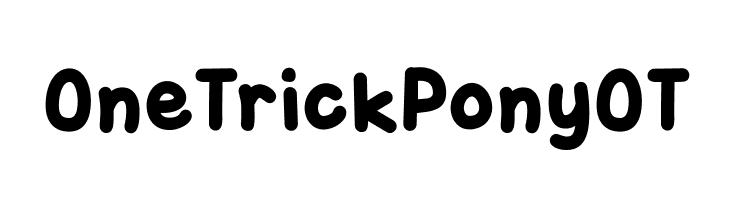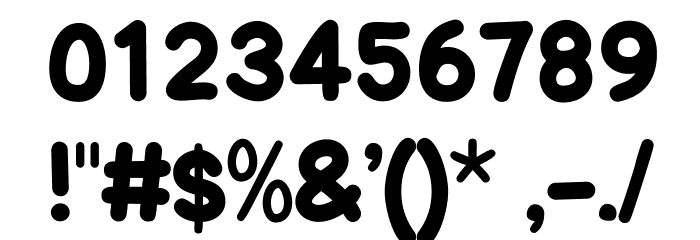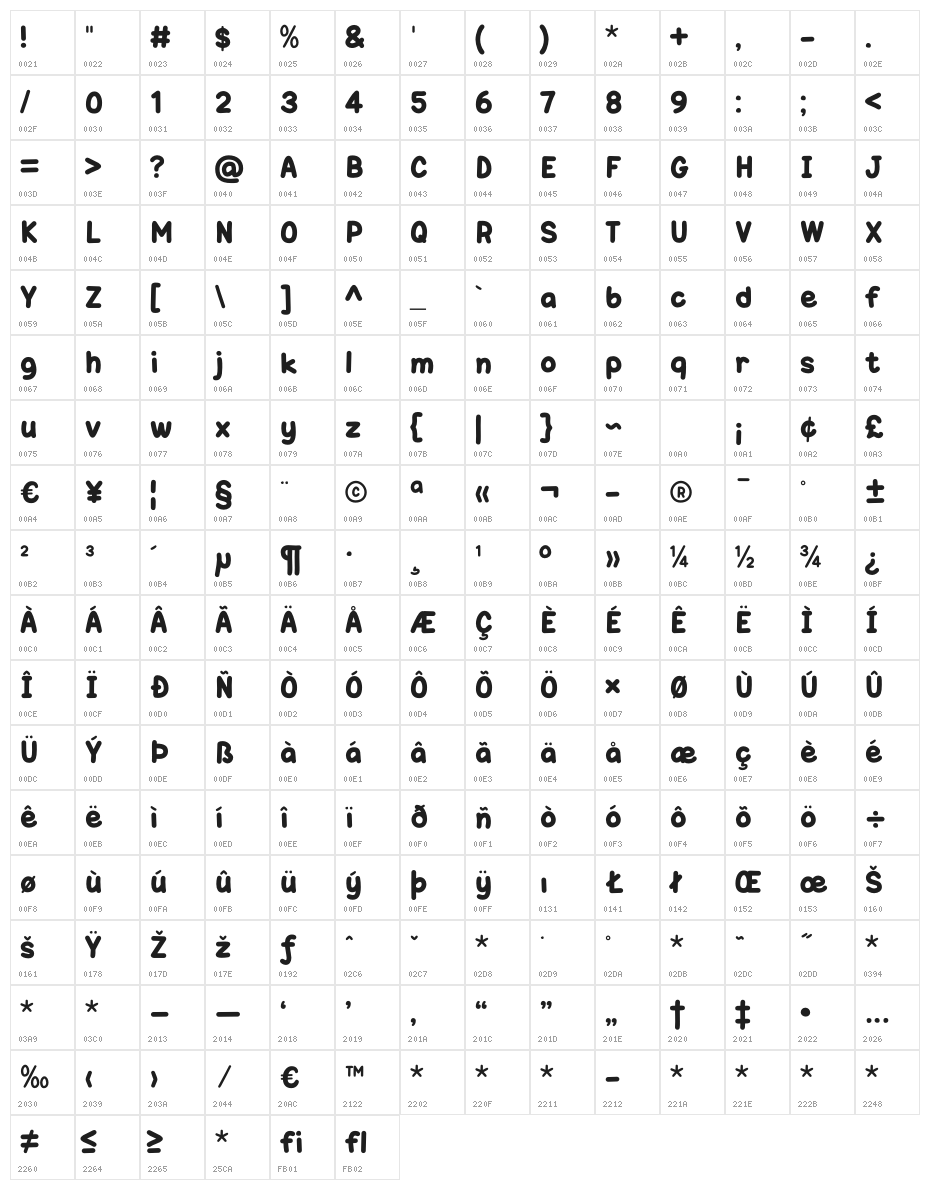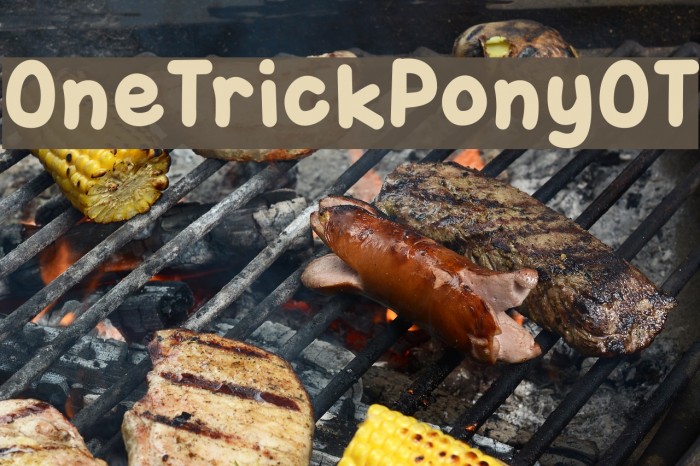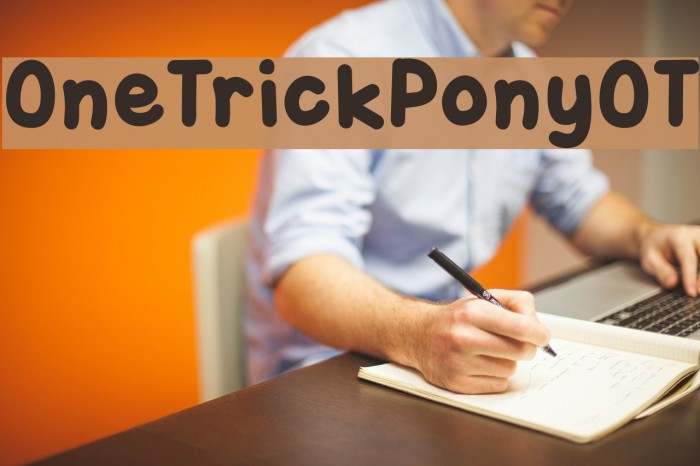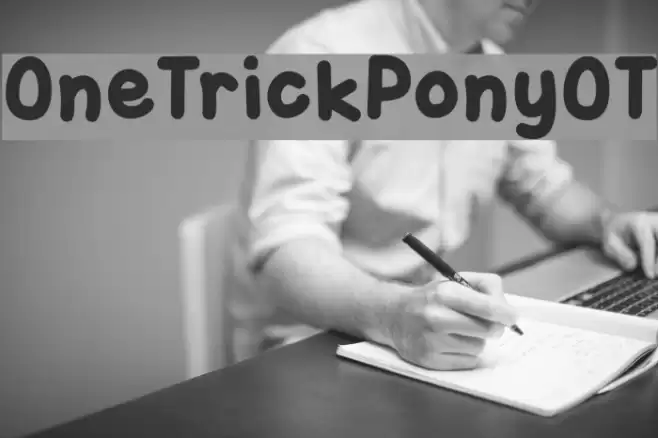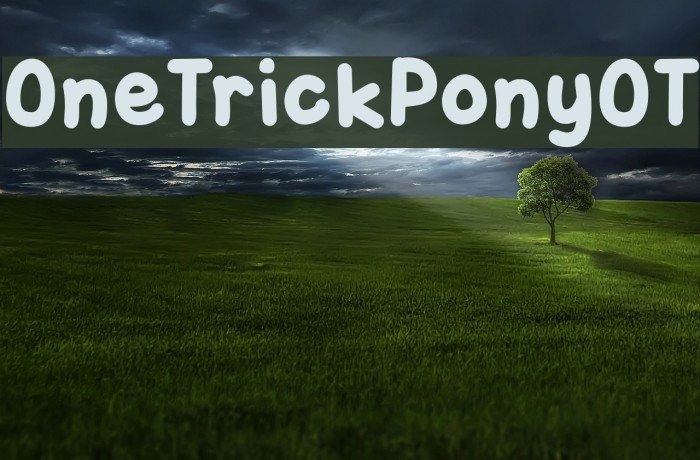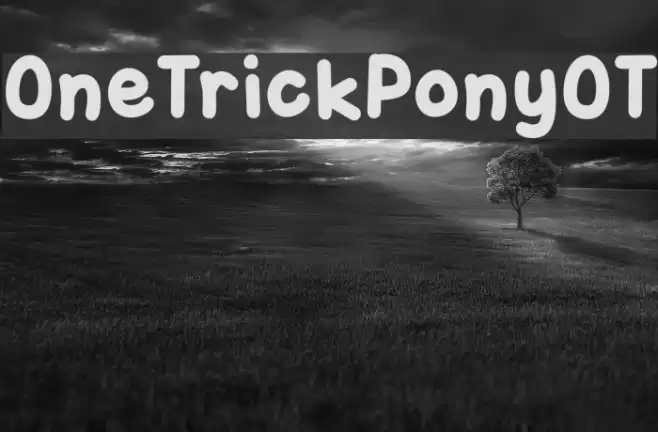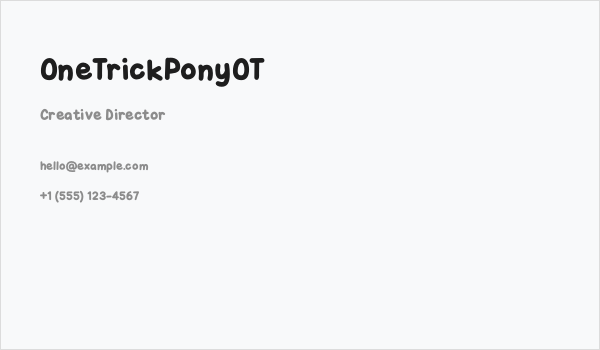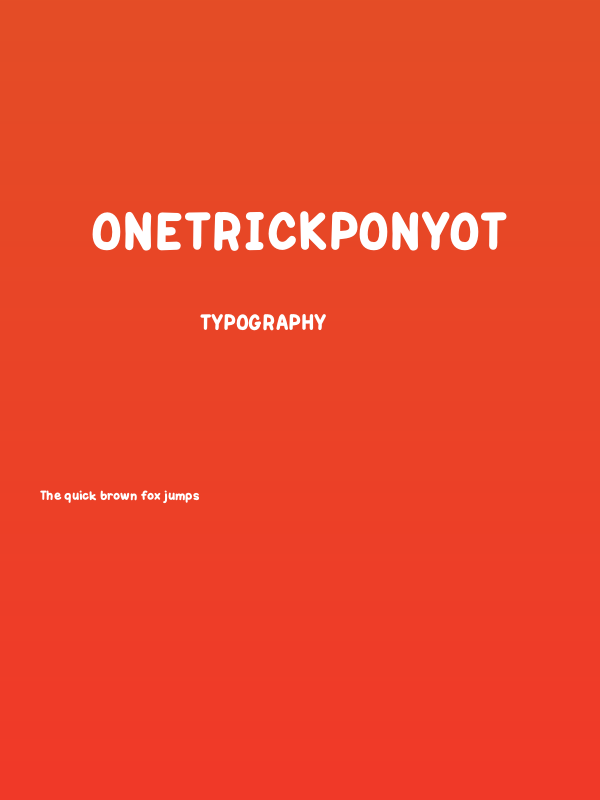
OneTrickPonyOT Font
| Style général | Playful |
| Cas d'utilisation | Headlines, Logos, Informal Text |
| Projets proposés | Ideal for children's books, playful branding, casual invitations, and social media graphics. |